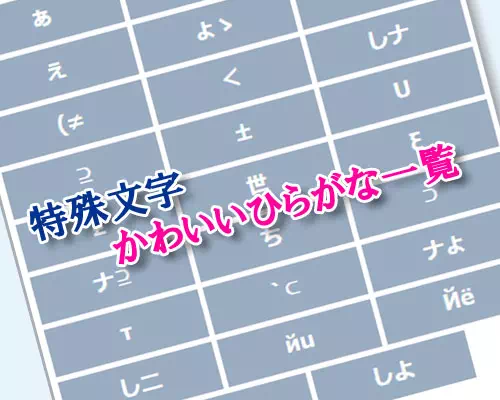
可愛いひらがなを簡単コピペ!特殊文字のへた字やギャル文字フォントも人気
特殊文字は英語だけでなくひらがなやカタカナも人気があります。
可愛いひらがなは『へた字』と呼ばれる特殊文字で、通常のひらがなよりも少し崩れた感じのフォントが手書き風で可愛い見た目になってます。
また、当サイトでは通常のへた字の他に少しめずらしい可愛いひらがな文字も紹介してます。
特殊文字はiphoneでは見れるが少し古いandroid端末では見れないというケースも多いです。
しかし、へた字やギャル文字はiphoneだけでなくandroidでも見れるので使っている方も意外と多いです。
通常のひらがなに飽きた時や見た目に少しインパクトを与えたい時などに使うと良いでしょう。
可愛いひらがな特殊文字一覧
可愛いひらがなと言えば以下のような特殊文字が人気です。
• へた字
• ギャル文字
• ひらがな囲み文字
とりあえず、以下にそれぞれの文字の一覧をまとめておくのでコピペしてXやインスタなどにご利用下さい。
ひらがな【へた字】の一覧
以下は特殊文字の『へた字』と呼ばれる可愛いひらがなの一覧です。
ひらがな【ギャル文字】の一覧
以下は特殊文字の『ギャル文字』と呼ばれる可愛いひらがなの一覧です。
ギャル文字はいくつか種類があるようですが、その中でも比較的使いやすいギャル文字の一覧です。
少しだけ見た目の違う別バージョンのギャル文字もあります。
特殊文字【ひらがな囲み文字】の一覧
以下は特殊文字の『ひらがな囲み文字』と呼ばれる文字の一覧です。
囲み文字はひらがなだけでなくカタカナの囲み文字もあります。
めずらしい可愛いひらがな
以下は通常の文字にはないオリジナルの可愛いひらがなです。
ひらがなの上や下に顔文字のようなものを付けることができます。
これらの可愛い文字は自分で自由に作ることができます。
※五十音すべて作ることができます
もちろん、インスタやTwitterのプロフィールなどにも使える文字なので珍しくて可愛い文字としておすすめです。
特殊文字のひらがなにはへた字やギャル文字が人気ですが、他の特殊文字も人気の文字が色々とあります。
例えば、ハートの特殊文字や天使の羽のような特殊文字なんかも人気ですね。
ハートの特殊文字、羽の特殊文字、リボンの特殊文字などはandroidでも見る事ができるので、androidスマホを利用している方がよく使ったりしているようです。
また、特殊文字と言えばやはり定番の英語の文字も外せません。
最近は可愛い特殊文字も増えてきているのでひらがなの文字と合わせてオシャレに見せる事ができます。
ツイッターやインスタのプロフィールや名前をかわいく見せるようにこれらの特殊文字を活用していきましょうね。
Instagramで可愛いひらがなを活用する方法
Instagramのプロフィールやストーリーズはフォントを工夫することで可愛らしい雰囲気を簡単に演出できます。
例えばプロフィール欄に「へた字風」のひらがなを使用することで親しみやすく柔らかい印象を与えることができます。
また、ストーリーズでは「ギャル文字風」など遊び心のあるフォントを取り入れると見た目がユニークになりフォロワーの注目を集めやすくなるでしょう。
文字の装飾を取り入れてあなたらしい個性を表現してみてください。
ストーリーズやリールでの活用例
ストーリーズでは質問機能やアンケート機能と組み合わせて可愛いフォントを使うと投稿全体のデザイン性がアップします。
特に手書き風フォントは柔らかな印象を与えるため日常の出来事やカフェ巡りの記録にぴったりです。
一方でリールでは短文のキャプション部分にアクセントとして「かわいいひらがなフォント」を使うと動画の雰囲気に合わせた統一感を演出できます。
ぜひ、ストーリーやリールに自分好みのフォントを活かしてみてください。
ひらがな以外の装飾文字も活用しよう
かわいいひらがな文字に加えて星やハートキラキラ記号植物モチーフの記号なども組み合わせるとより表現の幅が広がります。
たとえば「ありがとう」を「✿ありがとう✿」のように囲んだり「うれしい〜」の語尾に「💖」を添えるだけでも雰囲気が変わります。
本文ではひらがな装飾では記号というように用途を分けることで読みやすくて個性的な投稿になりますのでいろいろ試してみてください。
インスタやブログでの活用シーン
インスタのプロフィール欄では通常のフォントよりも柔らかい雰囲気のひらがなを使うことで可愛らしさや親しみやすさを演出できます。
投稿本文では語尾だけに可愛い文字を混ぜると読みやすさを保ったまま表情をつくれるでしょう。
ブログの場合は見出しの一部に使うと雰囲気がふんわりとするので手書き風のへた字やギャル文字をワンポイントにすると効果的です。
コメント欄や自己紹介ページでも活用しやすいため使う場所の雰囲気に合わせて文字を選んでみてください。
文字化けを防ぐための注意点
特殊文字を使う際はスマートフォンの機種やOSによって表示が変わることがあります。
iPhoneでは問題なくてもAndroid側で文字化けしたりブログのテンプレートによっては文字が欠けてしまうケースも見られます。
投稿前に自分の端末以外でも表示確認をしておくと安心でしょう。
また長文に多用すると可読性が下がるため見せたい部分に絞って使うのがおすすめです。
リンクや絵文字と組み合わせる場合は表示位置がずれないかも確認してみてください。
コピペ時の注意点と対策
可愛い文字は便利ですが環境によっては表示されないことがあります。
特に一部の特殊文字は機種やアプリによって文字化けする場合があります。
また日本語のひらがなは通常フォント変換ができないケースもあるため見た目が似た文字を使っている点にも注意が必要です。
インスタに貼り付けたあと実際に表示を確認することが大切です。
もし崩れている場合は別の文字に置き換えると改善することもあります。
安心して使うためにも投稿前に必ずチェックしておくと良いでしょう。
インスタで使える可愛いひらがなの活用方法
可愛いひらがなや特殊文字はコピペするだけでInstagramをはじめとしたSNSの印象を大きく変えられる人気の文字デザインです。
特にプロフィール名や自己紹介ストーリーズの文字装飾などで利用されることが多くおしゃれで個性的なアカウント作りに役立ちます。
またブログタイトルや見出しLINEの名前TikTokのプロフィールなどにも活用されており用途は年々広がっています。
ただし一部の特殊文字は利用するサービスや端末によって表示が異なる場合があります。
そのため多くの人に見てもらうプロフィールや投稿ではiPhone・Androidの両方で表示されやすい文字を選ぶと安心です。
用途に合わせて可愛いひらがなやギャル文字手書き風フォントを使い分けることでより自分らしいデザインを楽しめるでしょう。
気になる文字があれば実際にコピペして表示を確認しお気に入りのフォントを見つけてみてください。